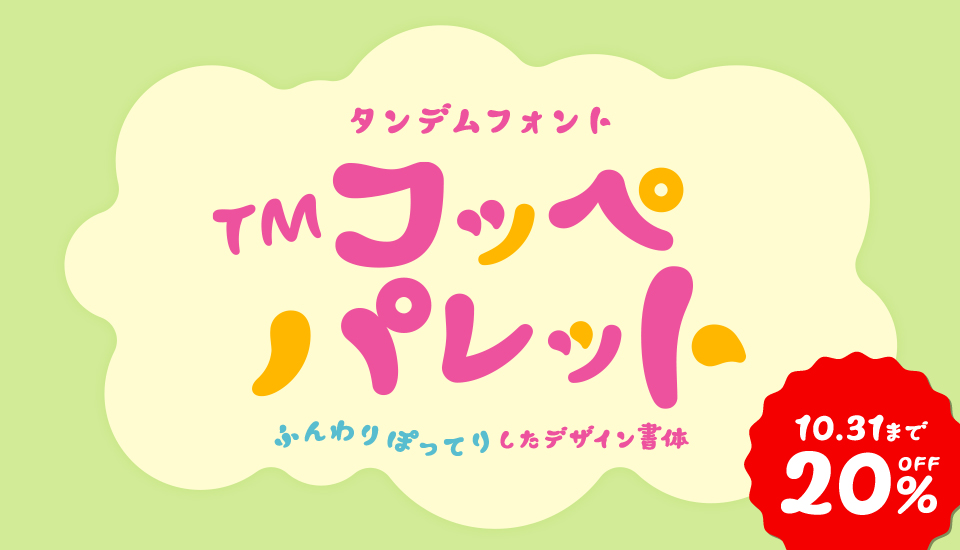
タンデムフォント TMコッペパレット
ふんわり・ぽってりしたリズミカルなデザイン書体
ぷるぷる、ポムポムした印象の太い書体を目指し、細部まで考えて作られたデザイン書体です。ふんわり・ぽってりして動きのある太めのTMコッペパレットは、見出しや、テロップなどに最適です。柔軟な使用許諾で、印刷物、WebサイトはもちろんYouTubeなどの動画も追加料金なしで利用可能です。ふんわり・ぽってりにこだわったTMコッペパレットについてご紹介していきます。
TMコッペパレットの特徴
ふんわり・ぽってりしたフォルム。漢字に比べて仮名は少し小さくデザインされ、動きのある、太めのデザイン書体です。
特徴的な「横線」を使い分け
太く、ぽってりしたエレメントをつけながら、左右のバランスをとるために、基本形の他に2種類のエレメントを使用。
① 基本形。始筆がぽってり太い ④ 太さを左右反転させることで狭いスペースを有効活用
② 重心のバランスをとるため、基本形とは反対に終筆を太く
③ 1文字につき1つ、隷書の波磔のような線で左に寄りがちなバランスを整える
ぽってりぷるんとした大きな「点」
ドロップ形のエレメントは、ポップでカワイイ雰囲気です。
画数と字形によって大きさを変えることで細部まで「ぽってり」
画数の多い漢字にも細部までぽってり感を表現できるよう、はじめに画数の大きい字形を字面枠目一杯に制作し、その後に仮名の仮想ボディを小さく設定。
組んでみると、コロコロと動きのある表情を見せます。
最大 平仮名の仮想ボディ くにがまえ 横長 縦長
縦書きでも「ぽってり」
絵本や、メニュー表など、組んでもちゃんと読めます。